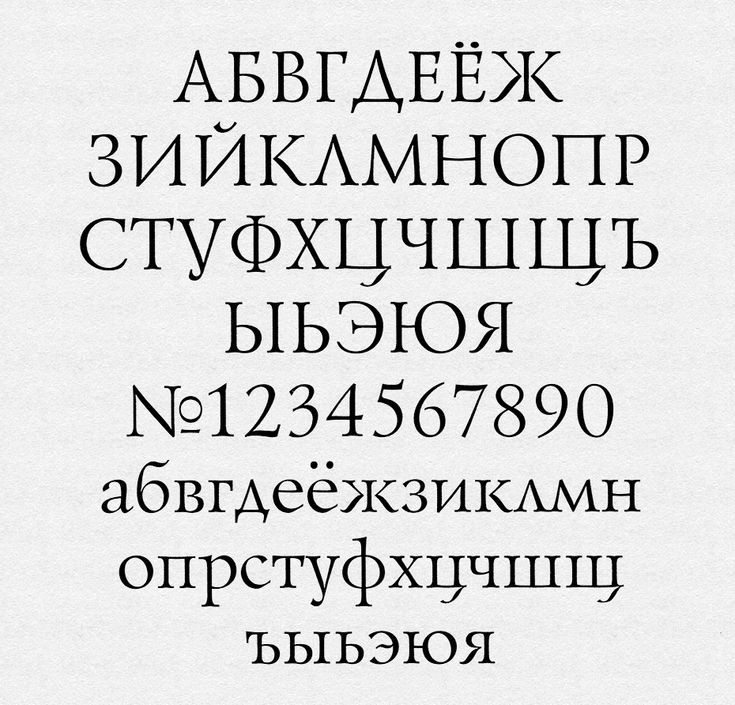
Наши шрифты с греческим
Магазин type.today специализируется на кириллице, но не ограничивается ей. В подтверждение этому показываем подборку наших шрифтов с поддержкой греческого
Элегантная гарнитура, подходящая для вёрстки книг и журналов. Brioni родилась спонтанно из практики работы с ширококонечным пером. Brioni была создана Николой Джуреком в 2008 году. В 2010-м Никола получил премию Icograda Excellence Award за гарнитуры Brioni, Plan Grotesque и Marlene.
Моноширинный гуманистический гротеск, который в отличие от «квадратных» шрифтов для кодинга, не повторяет пиксельную сетку, а наоборот — позволяет программистам забыть о её существовании. Codelia — шрифт с характерным (но не слишком) курсивом и палитрой начертаний от Light до Black.
В каждом — два файла: один — с лигатурами и другой — без. То, что Codelia задумана и нарисована как шрифт для кодинга, не мешает ей отлично работать в презентациях, айдентике и дизайне упаковки.
Fit, состоящий только из заглавных, заполнит любое пространство с максимальной плотностью, главное — правильно подобрать ширину. В палитре их целых десять, от Skyline до Ultra Extended плюс вариативный шрифт. Внутрибуквенные просветы и межбуквенные расстояния сохраняют свой размер вне зависимости от того, пользуетесь вы начертанием Extra Condensed или Extra Wide.
Input — коллекция, созданная, чтобы удовлетворить все типографические потребности программистов. Шрифты Sans (без засечек), Serif (с засечками) и Mono (моноширинный) помогут сделать сложную структуру кода яснее и визуально привлекательней, а ещё тонко намекнут на эстетику пиксельных шрифтов с экранов первых компьютеров.
Karloff исследует идею неразрешимых противоречий, ищет способ связать две противоположности в единое целое. В коллекции — три шрифта: новостильная антиква (Positive), эксцентричный «итальянский» шрифт с обратным контрастом (Negative) и результат их «скрещивания» (Neutral).
Изначально гарнитура Lava предназначалась для использования в журнальном деле, но далеко перешагнула границы задуманного применения. Это строгая и серьёзная рабочая лошадка, которая легко справляется со значительными объёмами текста. Она смотрится гармонично в малых кеглях, изысканно и элегантно — в крупных.
Типографическая система Parmigiano претендует на роль самой большой в истории коллекции шрифтов, вдохновлённых творчеством Джамбаттисты Бодони.
Семейство Parmigiano Text отличается изысканностью и плотнее по рисунку, чем начертание Headline. Эта универсальная гарнитура идеально подойдёт для набора журналов, книг и других длинных текстов, где важна лёгкость восприятия содержания. Нарисованная с прицелом на разборчивость и ровную читаемость, она обеспечивает комфортное, расслабленное чтение.
Proto Grotesk основан на немецком гротеске конца XIX века — того времени, когда ценилась яркость визуального языка. У него сложная родословная — здесь есть черты египетских и модернистских шрифтов, сочетаются округлые и острые формы, а в отдельных знаках появляются брусковые засечки. Несмотря на все эти противоречия, силуэт шрифта крепкий и прямолинейный. Характер у Proto Grotesk одновременно необычный и простой.
Универсальный рукописный шрифт с ярким характером, который будет уместен и на упаковке хипстерской простокваши, и на вывеске сёрферского бара в Гонолулу.
Это современный инструмент, использующий все возможности OpenType: лигатуры и альтернативные начертания делают набранный текст действительно рукописным, а еще работу дизайнера облегчают встроенные подчеркивания и контекстуальные начертания.
Умеренно ироничный, акцидентный гротеск с вариативным наклоном (помимо классического курсивного наклона, можно сделать обратный — разумеется, с любым углом). На графику и характер шрифта повлияла его многоязычность — демократичный и космополитичный, он сочетает в себе характерные особенности разных письменностей.
Греческий шрифт Брайля
Греческий шрифт Брайля это шрифт Брайля алфавит греческий язык.